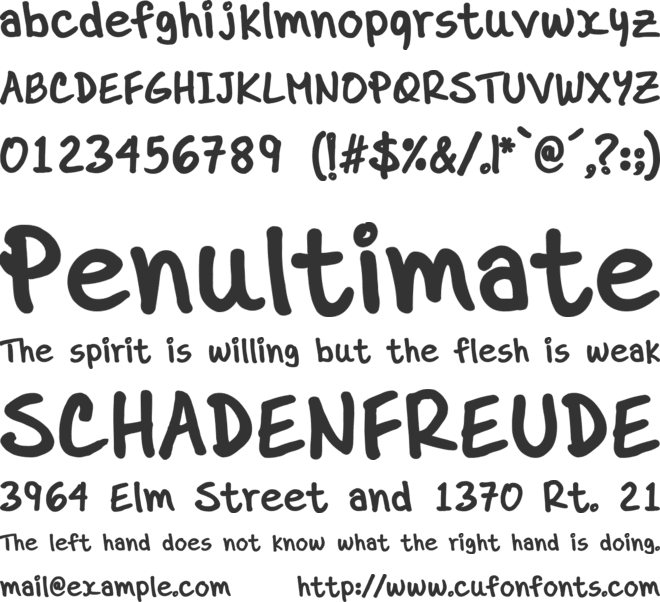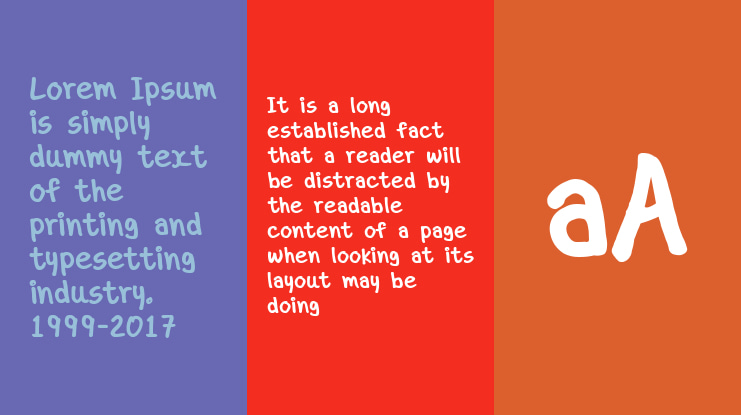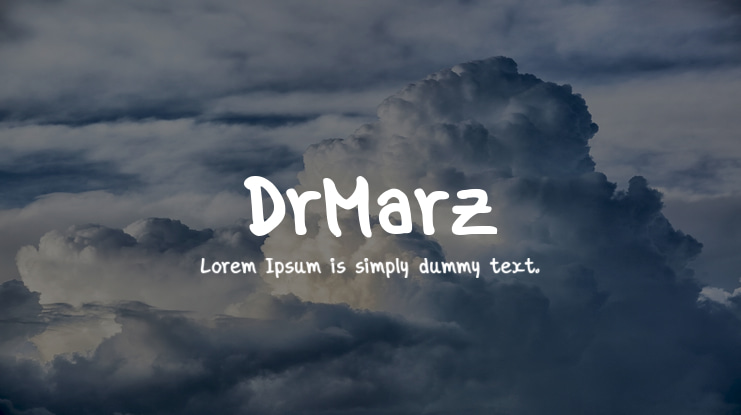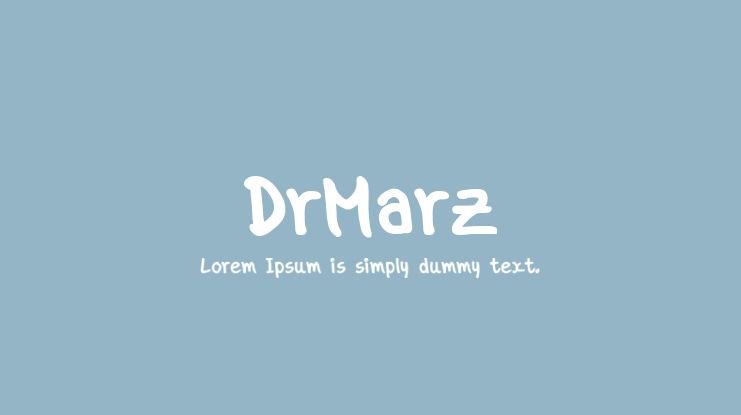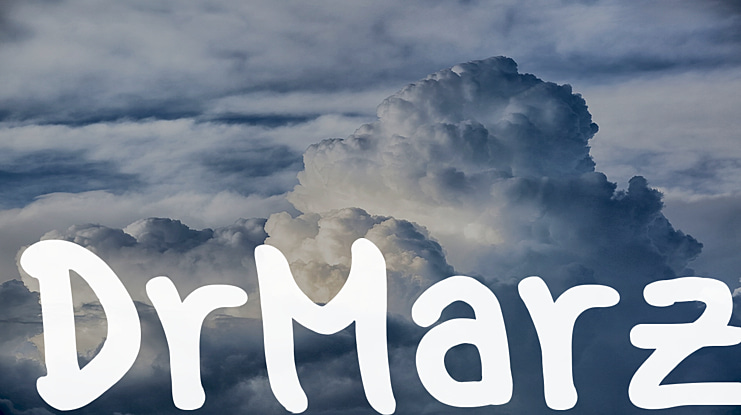
DrMarz Font Family
El conspiracionista Dr. Marz, cansado de los cayos en los dedos por escribir a mano sus libros y cartones, crea su propia fuente. Con estilografo y de su puño y letra , nace la caligrafia del autor. Perfecta para tus cartones, comics y otros proyectos informales que le puedas encontrar. visita mi sitio: www.todorius.com
Translated: The conspiracyist Dr. Marz, tired of the keys on his fingers for writing his books and cardboard by hand, creates his own source. With stylist and his handwriting, the author's calligraphy is born. Perfect for your cards, comics and other informal projects that you can find. Visit my site: www.todorius.com